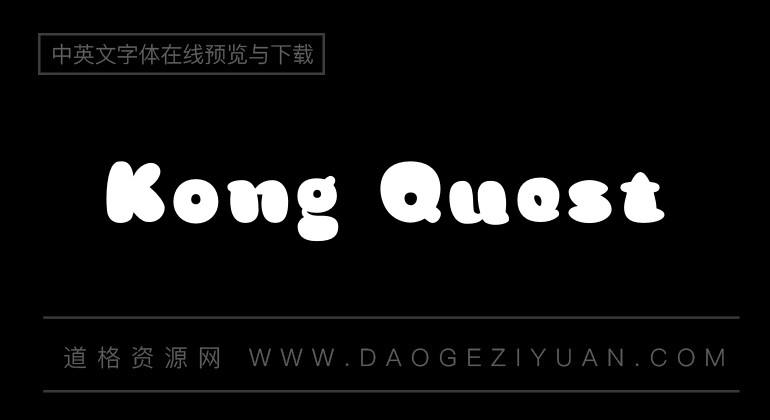
Kong Quest 字体是一款复古拼贴字体,由著名的设计师 Dan Zadorozny 创作。它是一款受到 80 年代游戏机游戏《Donkey Kong Country》启发而创作的字体,它具有粗犷的外观,充满活力和激情,令人印象深刻。Kong Quest 字体可以用于各种海报、书籍封面、T 恤衫、日历、卡片等设计中,可以带给你一种独特而充满活力的感觉。内容介绍
Kong Quest是一款非常不错的手写艺术字体,具有很好的视觉感,适合于文化类的宣传设计、商业类品牌的广告和产品包装设计以及个性化文字排版等较多场景。